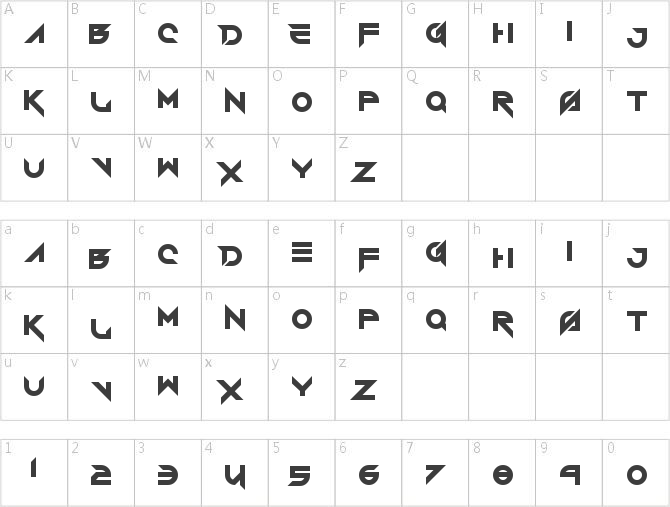
字體名稱: Vermin
Vermin Vibes Roundhouse
Vermin Vibes Roundhouse介紹
Vermin Vibes Roundhouse字體字庫是一款讓人賞心悅目、百看不厭的英文字體,適合各類廣告和產(chǎn)品包裝設(shè)計應(yīng)用,字體大小0.03MB,格式為ttf字體,上傳用戶是高塔。,作者/版權(quán)方為未知